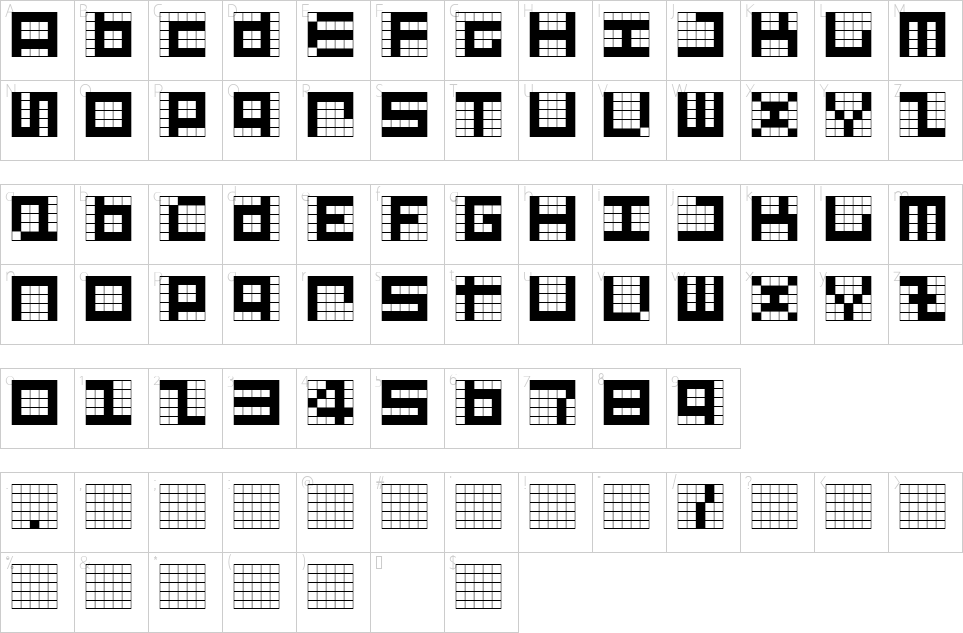
Descubra a simplicidade e a elegância do Give Me 5 Font, uma opção gratuita para designers e amantes de bom gosto que valorizam facilidade e legibilidade. Desenvolvida pelo designer Manfred Klein, esta fonte é perfeita para aqueles projetos simples que exigem um toque contemporâneo. Com apenas cinco sílabas, o Give Me 5 atende às necessidades de designers buscando uma opção sem compromisso em seu portfólio de fontes gratuitas. Download a versione para Windows e Mac do Give Me 5 Font hoje e experimente essa maneira elegante de estilizar qualquer texto!